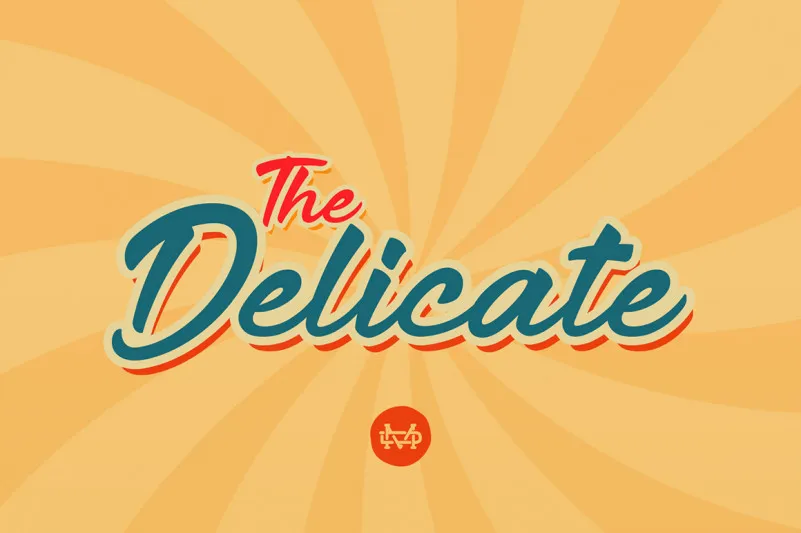
The Delicate Script Font – Download Grátis
A fonte The Delicate é uma introdução fascinante para os designers que buscam uma script elegante e forte, perfeita para projetos variados. Esta fonte Brush Fonts apresenta nuances suaves e detalhes delicados, adequada para criar designs notáveis e personalizados. O designer madeDeduk criou The Delicate com habilidades de pontilhamento refinadas que oferecem uma experiência visual única em seus designações. Com sua elegância natural e características detalhadas, a fonte The Delicate é perfeita para textos como nomes de empresas, logotipos, ou até mesmo para criar um texto em evento especial. Seja você criando mensagens amigáveis em seu site, inserindo rótulos em embalagens de produtos, ou desenhando uma mensagem única para seu próximo projeto gráfico, a fonte The Delicate estará sempre à mão para agregar o toque final.